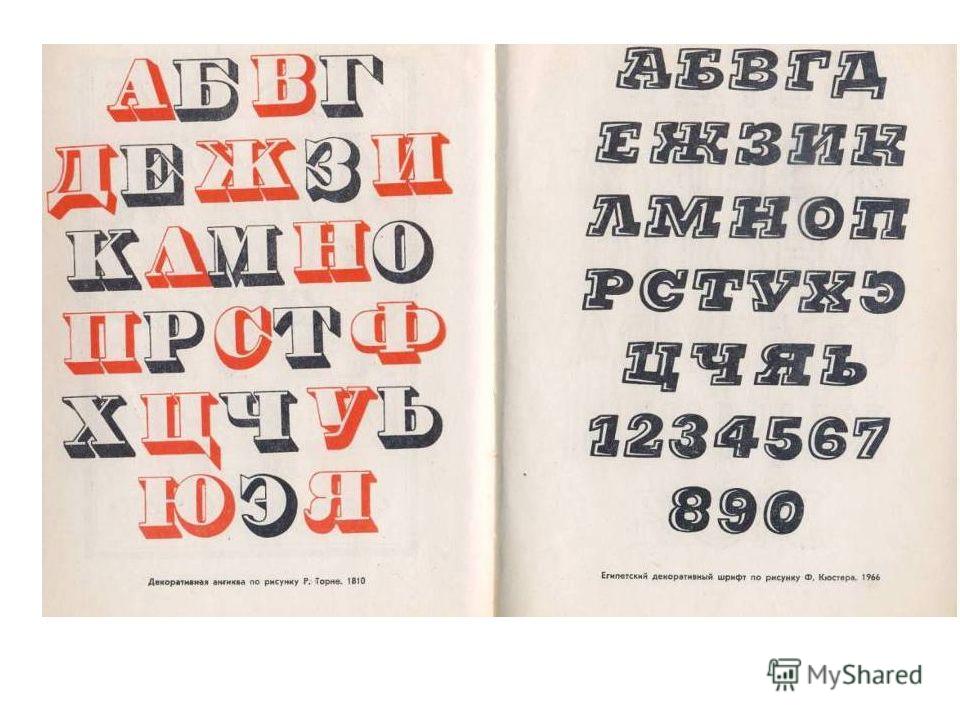
Буквы разными шрифтами: Шрифты для ников онлайн, красивые буквы
Владимир Фаворский
аша русская шрифтовая система одна из европейских систем, идущая отчасти от греческой, в выражении и оформлении своих функций очень сильно использует вертикаль и горизонталь со всеми их свойствами.
Причём можно сказать, что и горизонталь как линия равномерного движения, и вертикаль как ограниченная, остановленная линия, могущая иметь свой определённый внутренний строй и отсюда свой определённый масштаб, выявляют в нашем шрифте все основные свойства.
Горизонталь составляет основу строки, функция движения по тексту, в частности по строке, использует свойства горизонтали, её равномерное движение, и естественно и увлекательно вместе с буквами идёт по ней. С другой стороны, вертикаль столбца даёт нам и цельность этого столбца, когда мы его воспринимаем статически, и, читая строку за строкой, мы спускаемся по ней все ниже и ниже, и, между прочим, это движение вниз по вертикали, идя как бы против течения, идущего снизу, и имея тем самым всё время упор, может быть всегда остановлено. (Это подобно тому, как пароход, положим, на реке Оке, идя против течения, легко останавливается и задерживает ход и ссаживает пассажира, а идя по течению, часто отказывается это сделать.)
Но вертикаль со всеми её свойствами как ограниченной и масштабной линии работает в шрифте главным образом как остановка.
Оформление этих двух основных моментов в шрифте и составляет главное, и в этом вертикаль и горизонталь играют первостепенную роль.
В. Фаворский. «Шрифт, его типы и связь иллюстрации со шрифтом». Обложка. 1925. Ксилография.
Если взять слова нашего языка, то для всех ясно, что они не безразличны к содержанию своему и являются большею частью живыми словесными изображениями тех вещей, которые они обозначают.
Не являются ли буквы тоже сколько-то подлинным изображением тех голосовых жестов, которыми мы при помощи горла, нёба, зубов и языка произносим нужный нам звук?
В этом отношении можно по-разному расценивать гласные и согласные звуки. Гласные гораздо проще по мускульному жесту; тут участвует главным образом голосовая труба, которая либо сжимается, как в звуке «И», либо берётся открытая в самой своей глубине, как в звуке «А», либо удлиняется ртом в звуке «О», либо удлиняется губами в звуке «У».
Современный шрифт неотрывно связан с понятием компьютерного шрифта (угадайте почему). Он более строгий, чем его предшественники, и для него характерны прямые засечки и резкий контраст. В резком контрасте кроется и его слабость — он отлично подходит для заголовков и крупных надписей, но для написания длинных текстов он не слишком удобен.
Современный шрифт — это файл, который содержит в себе векторные и растровые начертания ПРОПИСНЫХ и строчных букв, цифр (от 0 до 9) знаков пунктуации (точки, запятые и их совместные комбинации, знаки вопроса и ударения) и прочие знаки.